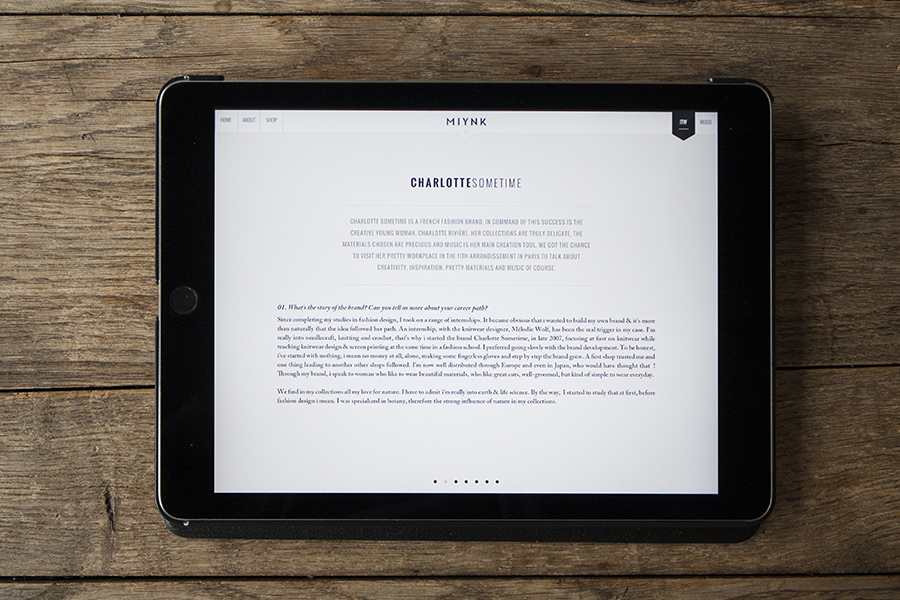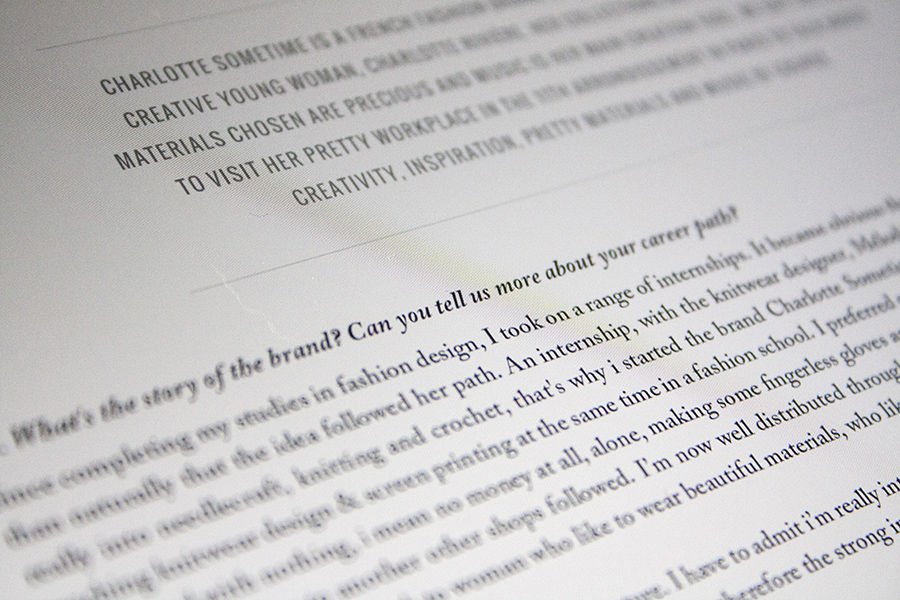
App der Woche #3: Miynk, das DIY-Magazin
Miynk App Tablet Magazin für DIY
Die wunderschöne Miynk-App aus Frankreich schlummert schon etwas länger auf meinem Tablet. Das DIY-Magazin bietet Anleitungen zum Selbermachen aus den Bereichen Kochen, Spielen, Dekorieren, Mode und Beauty. Man kann das Magazin komplett kaufen oder sich einzelne Rubriken zusammenstellen. Für diesen Artikel habe ich (nicht ganz uneigennützig) die Rubrik „Dekorieren“ gekauft. Leider gibt es bisher nur diese eine Ausgabe, sodass ich bei fast sommerlichen Temperaturen die Ausgabe für Winter 2013/2014 präsentiere. Eine frische Brise ist also garantiert.
Angenehm verträumt
Auf der Startseite der Miynk-App kann man die Rubrik auswählen. Jede Rubrik hat kostenlose Probeanleitungen, sodass sie einen guten Einblick bekommen, ohne direkt bezahlen zu müssen. Das zarte Farbschema und die pastelligen, angenehm verträumt wirkenden Bilder sind ästhetisch sehr anziehend. Zugegeben: Ich, weiblich, unter 40 und mit Hang zum Selbermachen gehöre auch absolut in die Zielgruppe. Bitte sehen Sie es mir also nach, wenn ich hier etwas schwärmerisch werde.
Miynk App Tablet Magazin für DIY
Schön einfach, einfach schön
Steigt man in eine Rubrik ein, kann man sich in der Leiste unten eine Anleitung aussuchen. Die Navigationsstruktur ist klar und ohne weitere Erklärungen gut zu verstehen. Interaktivität wurde in der Miynk-App auf ein Minimum reduziert, wohl um die stille Anmutung der App nicht zu stören. Die einzige „auffällige“ Animation begrüßt Sie beim Startbild einer jeden Anleitung: Zuerst wird das Bild vollflächig angezeigt, dann stark weichgezeichnet, um anschließend die Typografie und den Start-Button zu platzieren. Simpel und schön.
Miynk App Tablet Magazin für DIY
Lediglich beim Startbild einer DIY-Anleitung setzt Miynk auf Animationen. Die sind ebenso schlicht wie schön.
Der einfache und sehr grafische Aufbau geht bei den Anleitungen weiter. Die benötigten Materialien präsentieren sich übersichtlich in strenger Anordnung, durch Wischen oder Fingertippen auf die Ziffern unten gelangen Sie zum nächsten Schritt.
Miynk App Tablet Magazin für DIY
Was Sie für Ihr DIY-Projekt benötigen, zeigt Ihnen Miynk in einer solchen Anordnung.
Miynk App Tablet Magazin für DIY
Um durch die Anleitung zu navigieren, wischen Sie einfach mit dem Finger über den Bildschirm. Oder Sie tippen auf die Ziffern am unteren Rand der Miynk-App.
Moods als Inhaltsverzeichnis
Die Moods sind eine interessante Alternative zum klassischen Inhaltsverzeichnis. Anstatt einer Auflistung aller verfügbaren Anleitungen, sehen Sie ein Ensemble aller DIY-Produkte. Über die Plus-Symbole gelangen Sie zu den entsprechenden Artikeln.
Miynk App Tablet Magazin für DIY
Statt eines langweiligen Inhaltsverzeichnisses, gibt Ihnen Miynk durch ansprechende Moods einen Überblick über die zur Verfügung stehenden DIY-Anleitungen.
Miynk App Tablet Magazin für DIY
Mit einem Klick auf das Plus-Symbol gelangen Sie dann zum jeweiligen Thema.
Typografie: reizvoll und unleserlich?
Bei den Interviews merkt man, dass die Schriftmischung sehr feinfühlig gewählt wurde. Bei der Serifenschrift hat vor allem die Kursive bezaubernde Details, wie zum Beispiel ein stark geschwungenes Fragezeichen. Die hochgewachsene serifenlose Schrift steht in einem wirkungsvollen Kontrast dazu. Ich frage mich nur, ob die Serifenschrift auch auf iPads ohne Retina-Display gut lesbar ist. Sie ist sehr, sehr klein und hat eine enorme Zeilenlänge im Fließtext. Ohne Frage ist das grafisch sehr reizvoll. Was die Leserlichkeit angeht, ist man hier aber vielleicht über das Ziel hinausgeschossen.
Miynk App Tablet Magazin für DIY
Die Fließtext-Schrift ist ziemlich klein und hat eine enorme Zeilenlänge. Auf einigen Geräten könnte das die Lesbarkeit negativ beeinflussen.
Miynk App Tablet Magazin für DIY
Dafür punktet die Schrift jedoch mit schönen Details, was perfekt zum ästhetischen Gesamtbild der Miynk-App passt.
Fazit
Miynk ist die erste App in diesem Blog, die keinen Print-Vorgänger hat. Dadurch funktioniert sie losgelöst vom klassischen Aufbau und der Dramaturgie eines Magazins mit Editorial, Lesermeinungen und Titelstory. Lediglich das Interview hat sie sich beim Magazinformat geliehen. Miynk versteht sich deshalb durchweg als reines App-Magazin und ist ein gutes Beispiel für ein neues, experimentelles Format.